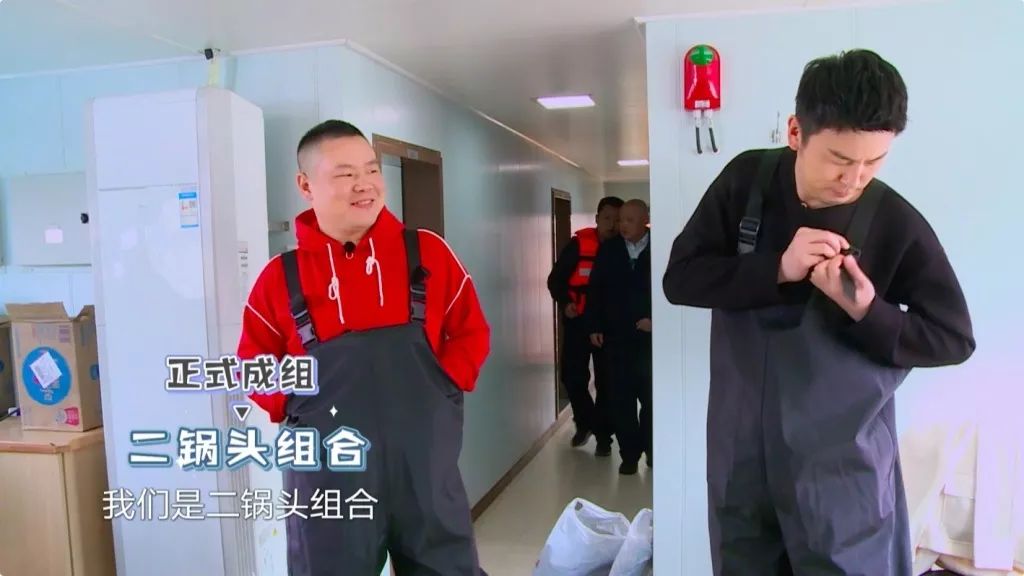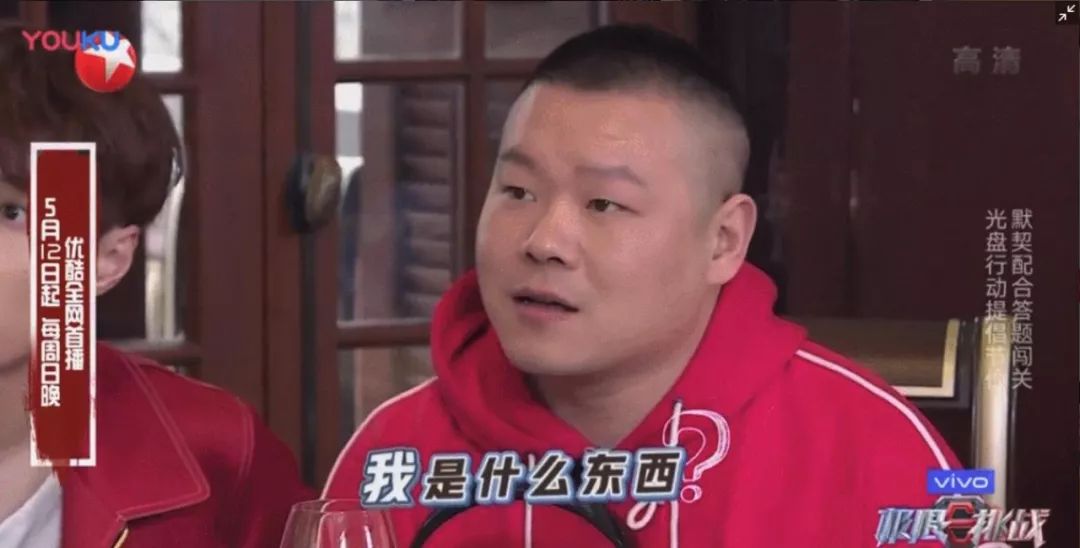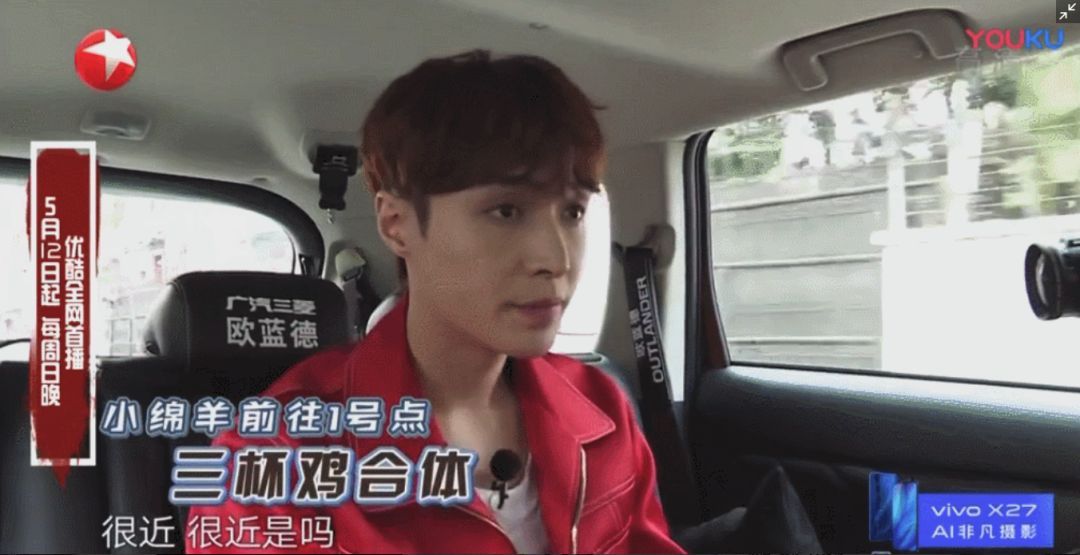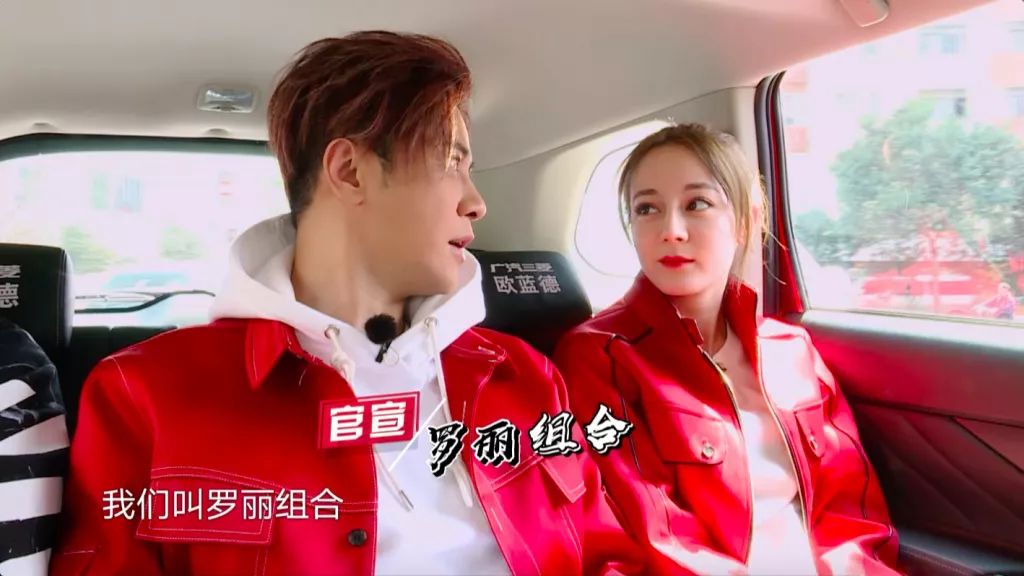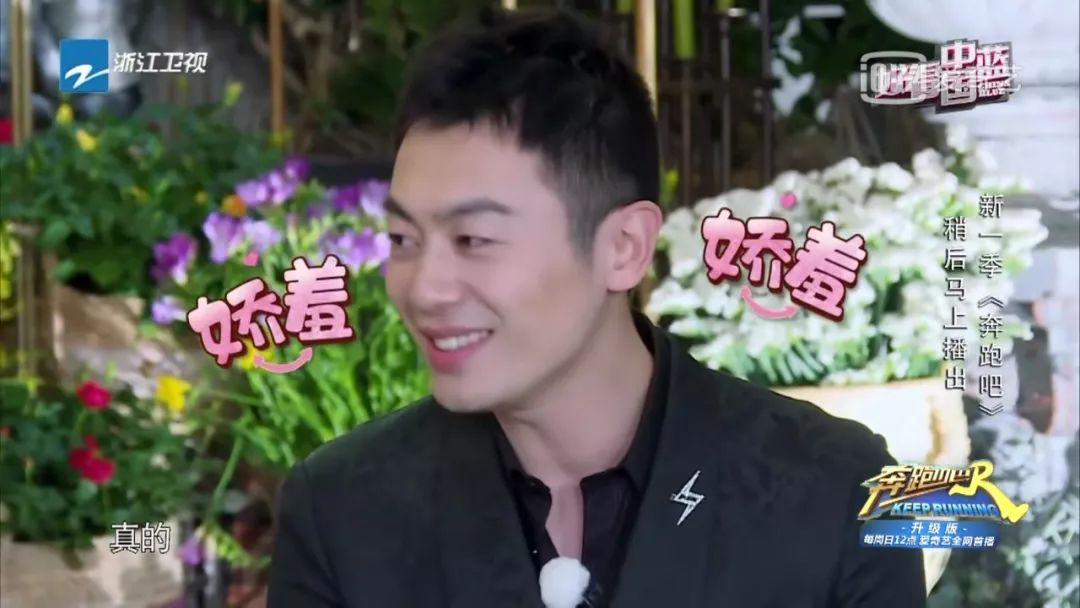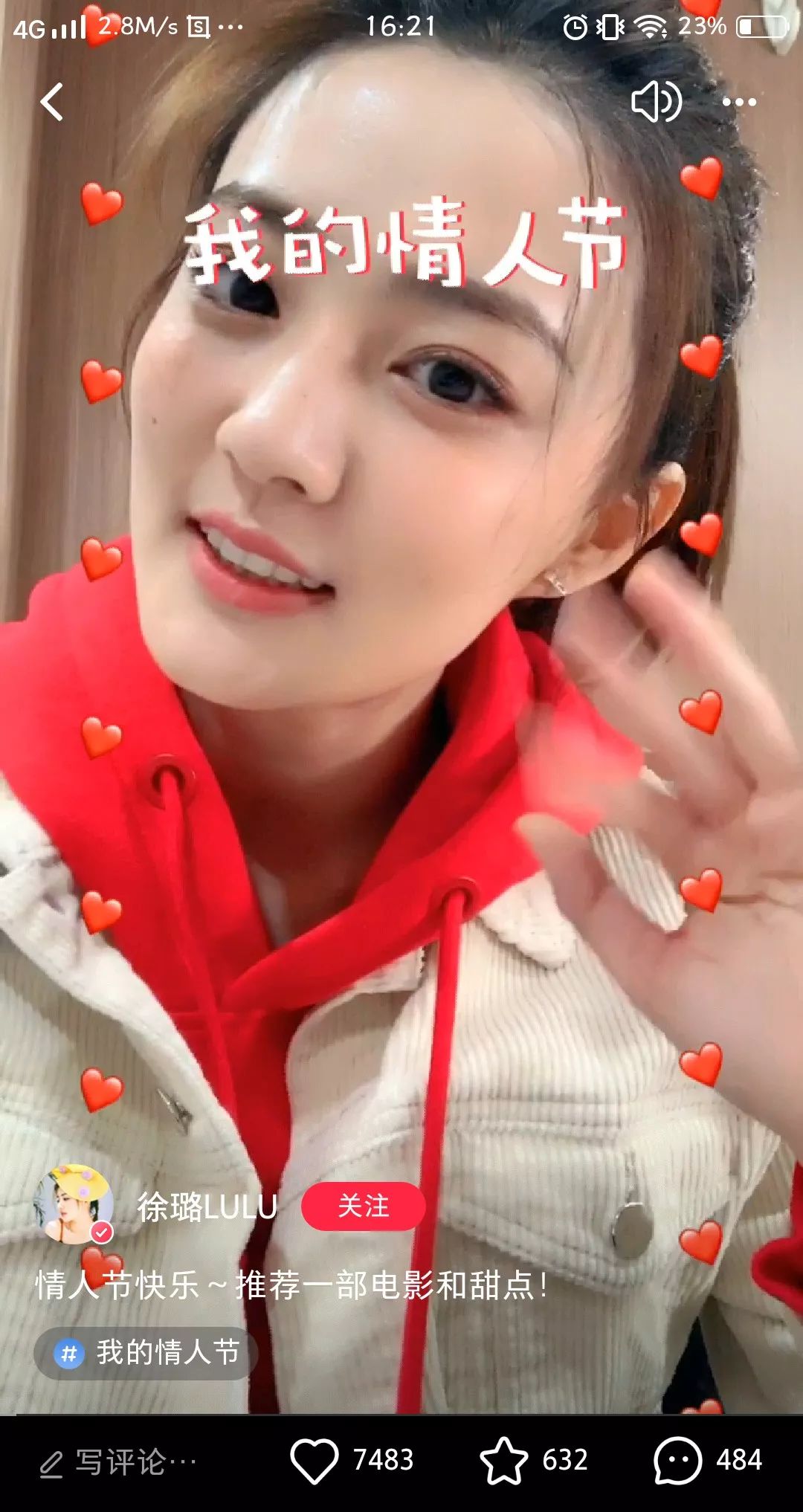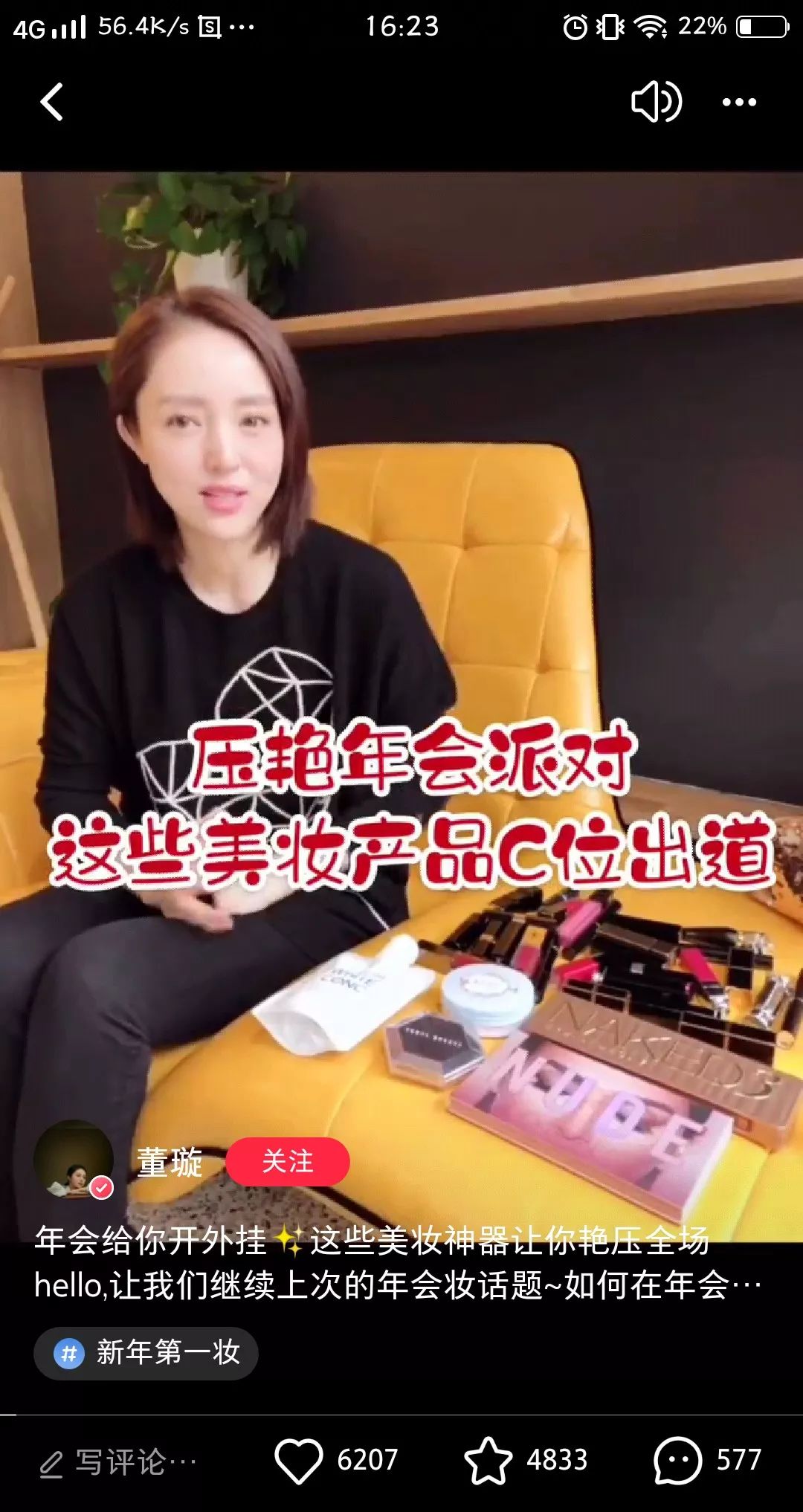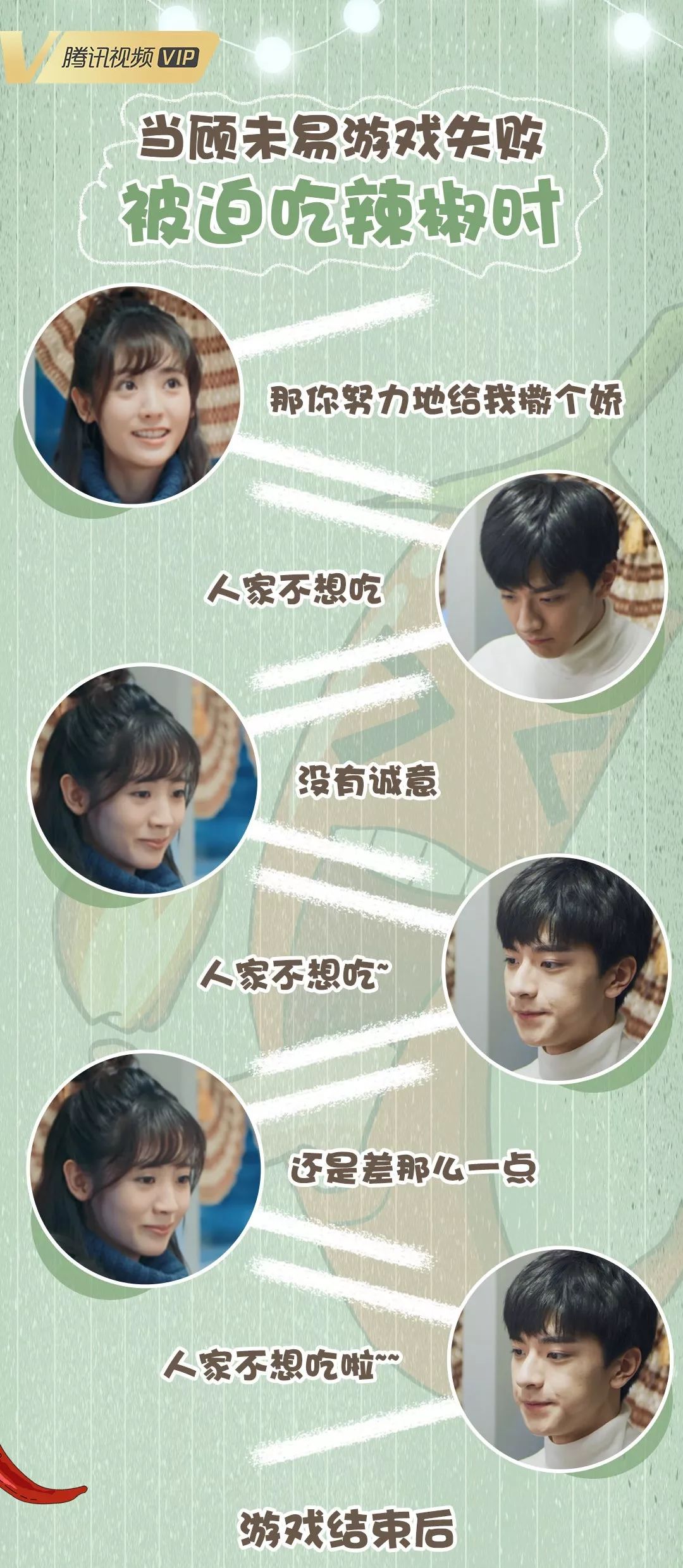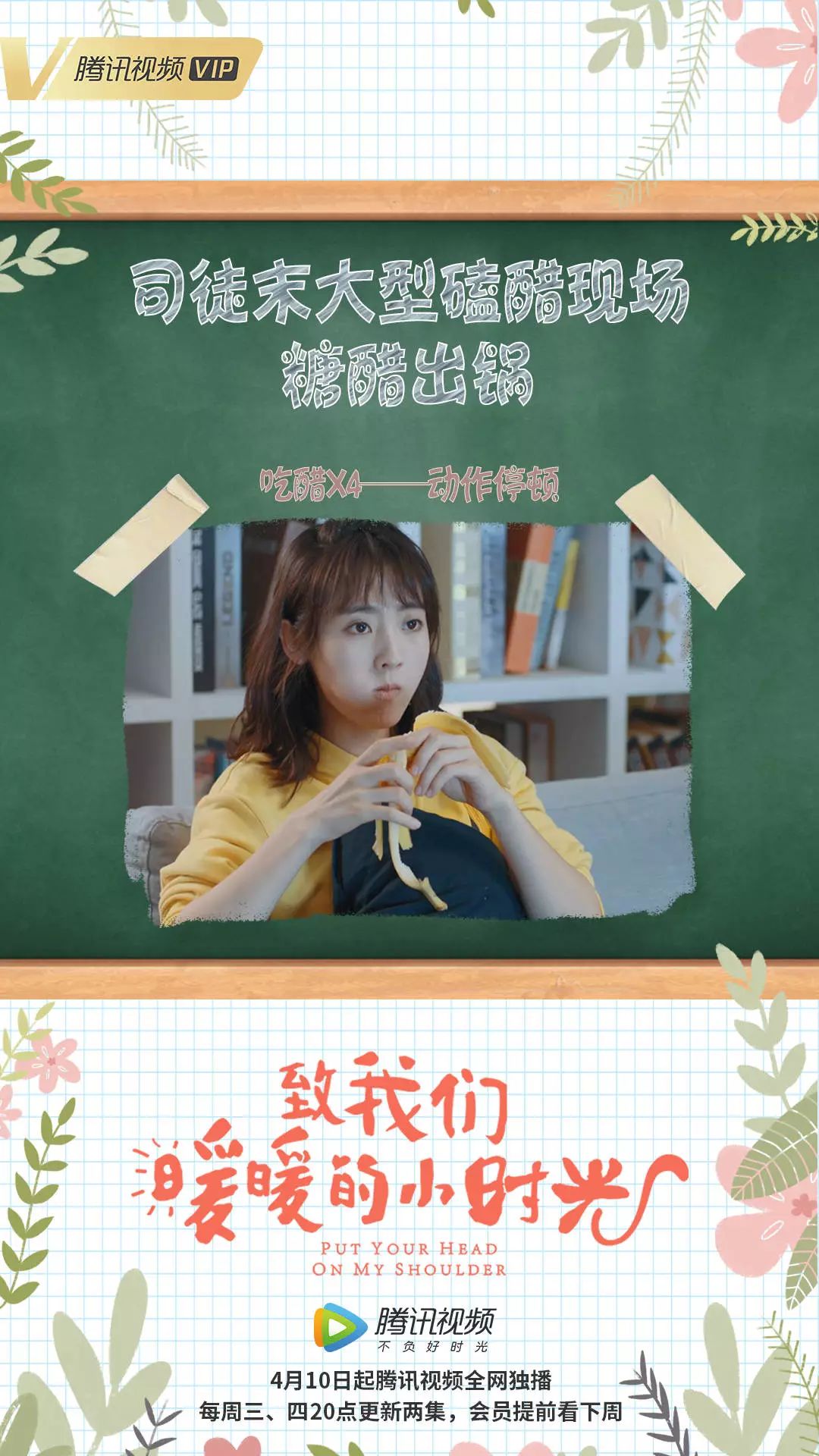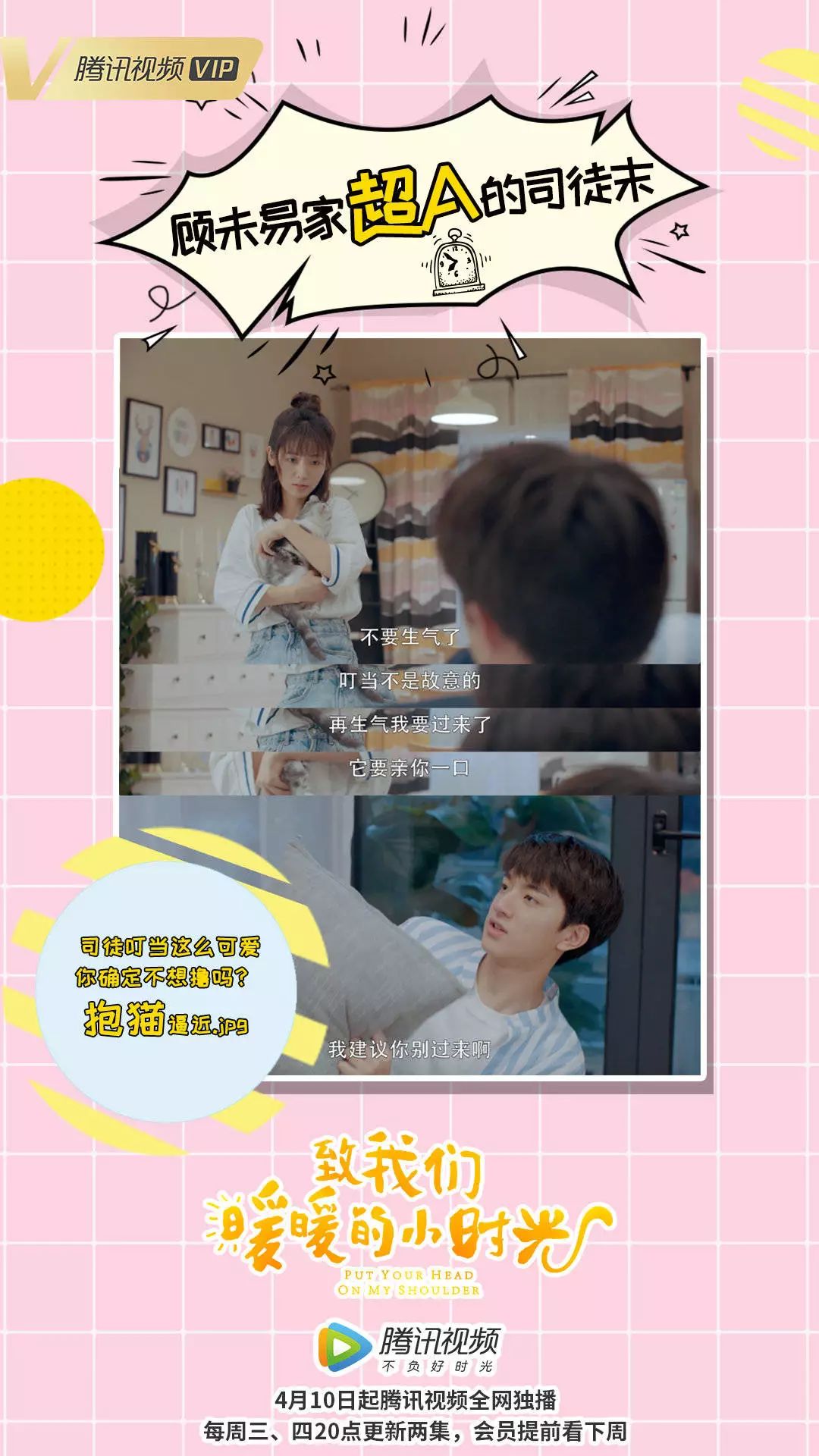
适合综艺的花字字体分享,如果综艺没有花字,我们会失去多少哈哈哈……
对柚子来说,周末最幸福的就是追剧,看综艺,抛开一切烦恼,尽情姨母笑,哈哈哈~
不过看着看着,还有意外收获呢,各种花字,它不认识我,我可认识它。就拿昨晚的极限挑战来说,汉仪趣黑大量出现~
还有“三杯鸡合体”的汉仪菱心体~
小岳岳神回应的的汉仪雅酷黑~
不止这些,眼尖的我,还发现了很火的汉仪尚巍手书、汉仪铸字木头人、汉仪喵魂体等,给这七个戏精加了不少戏。
除了《极限挑战》,其它综艺也是一个比一个天马行空~
▲汉仪天宇风行体
▲汉仪喵魂自由体
▲汉仪糯米团
▲汉仪铸字木头人
▲沐瑶软笔手写体
▲汉仪阿尔茨海默病体
▲汉仪晓波折纸体
▲汉仪星球体
如果你觉得只有在综艺上,看到百字齐放,那就错了,社交媒体才是它们真正的聚集地。
▲汉仪跳跳体
▲汉仪字研卡通
微博更是爆发地,比如高甜收官的末未夫妇。
▲汉仪太极体
▲站酷快乐体
▲华康海报体
还有跑男的“澡堂惊魂记”~
▲汉仪铸字童年体
这么多花字,足以撩动你所有的喜怒哀乐,但也不是越多越好,看看鼻祖日韩~
一个画面一种就够了,两种要看彼此的搭配,三种以上就没法看了……
还有就是情绪的引导要到位,说白了就是该出现出现,不该出现的时候不要刷存在感~